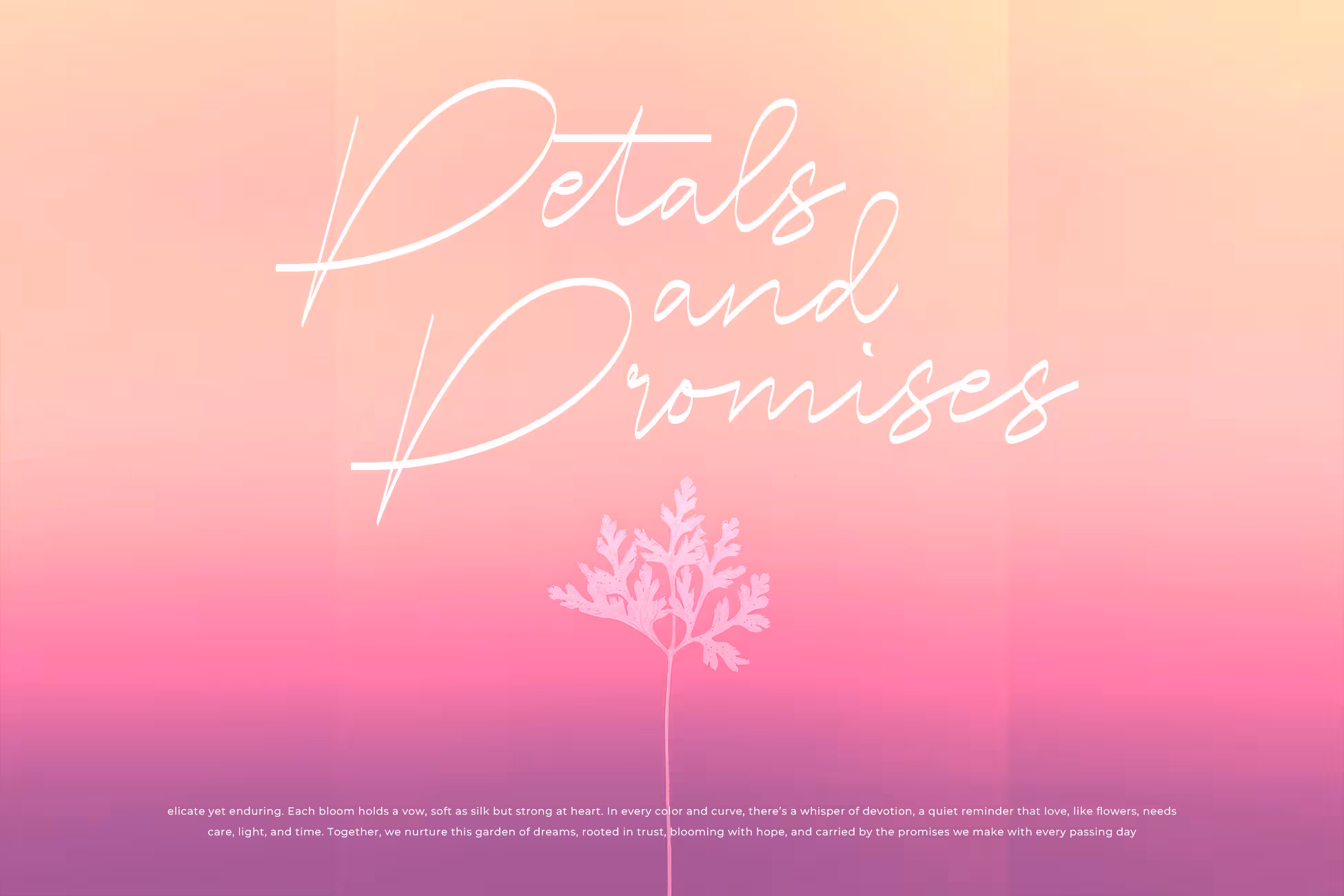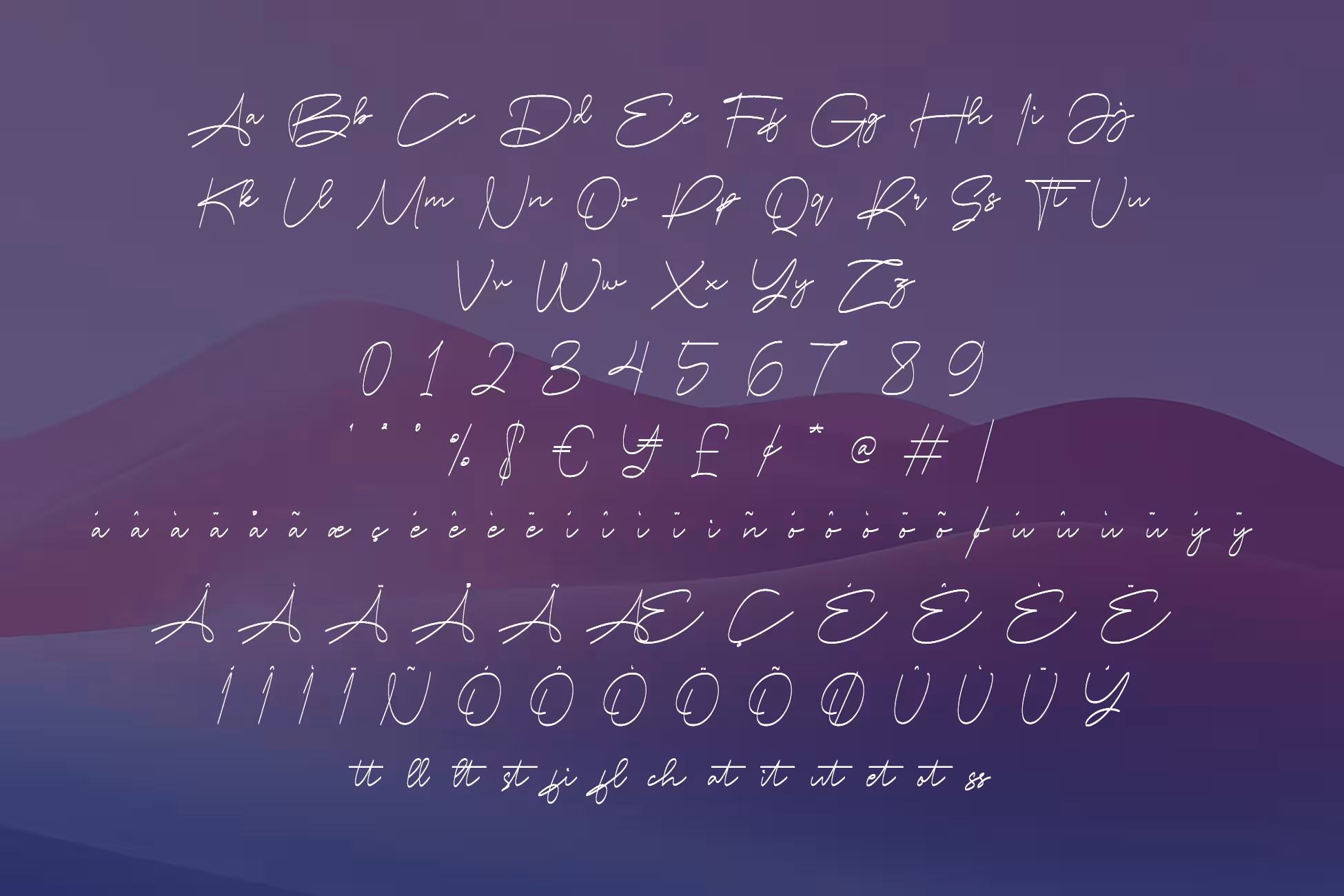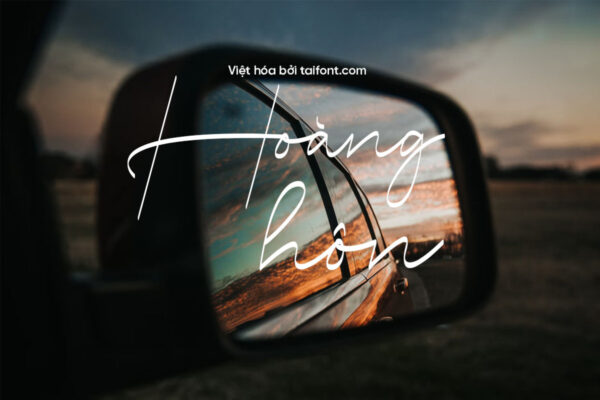
Giới thiệu về Font TF Helroty Việt hóa
TF Helroty Việt hóa là một font chữ viết tay (script font) mang vẻ đẹp tự nhiên, phóng khoáng và đầy cá tính. Với những đường nét được thiết kế như chữ viết tay thật, Helroty tạo cảm giác thân thiện, gần gũi và rất riêng biệt, lý tưởng để thêm dấu ấn cá nhân vào các tác phẩm của bạn.
Font này là lựa chọn tuyệt vời để bạn thể hiện sự sáng tạo và làm cho những bức ảnh thêm phần sống động:
- Viết các câu thú vị lên ảnh: Hoàn hảo để thêm những câu trích dẫn, slogan, lời chúc, hoặc những dòng tâm sự lên ảnh cá nhân, ảnh du lịch, hoặc ảnh chia sẻ trên mạng xã hội. Helroty sẽ làm cho những dòng chữ trở nên cuốn hút và đầy cảm xúc.
- Thiết kế thiệp mừng, thư ngỏ: Mang lại sự chân thành, thân mật và cá tính cho những thiệp mời, thiệp chúc mừng, hoặc thư cảm ơn.
- Thiết kế bao bì, nhãn mác handmade: Phù hợp cho các sản phẩm thủ công, quà tặng tự làm, tạo cảm giác độc đáo và được chăm chút.
Với TF Helroty Việt hóa, bạn có thể dễ dàng biến những bức ảnh hay thiết kế đơn giản thành những tác phẩm nghệ thuật đầy ý nghĩa và phong cách.